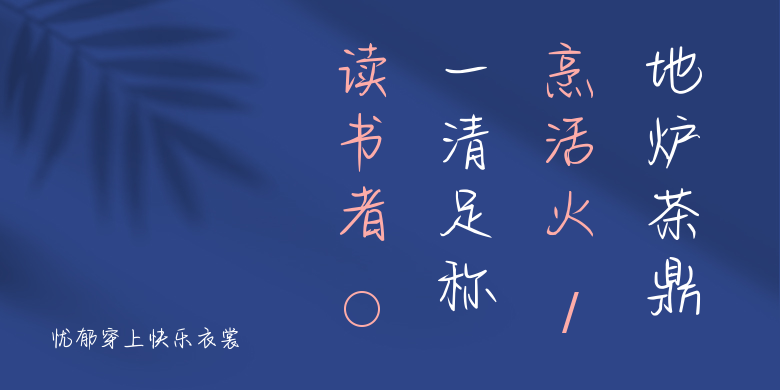
忧郁穿上快乐衣裳
忧郁穿上快乐衣裳,这款字体结构工整、笔画清晰,兼顾美观与易读性,适用于标题、正文、海报、包装、LOGO 等多种场景。字形优雅稳定,风格百搭耐看,适配日常排版与创意设计,让文字呈现更舒适、更具质感。忧郁穿上快乐衣裳一笔一画,皆是细节,以均衡的比例、流畅的线条打造舒适视觉体验,字形端正大气,风格简约现代。无论是商业设计、品牌宣传还是日常排版,都能轻松驾驭,让文字更有格调与力量。忧郁穿上快乐衣裳字体下载。